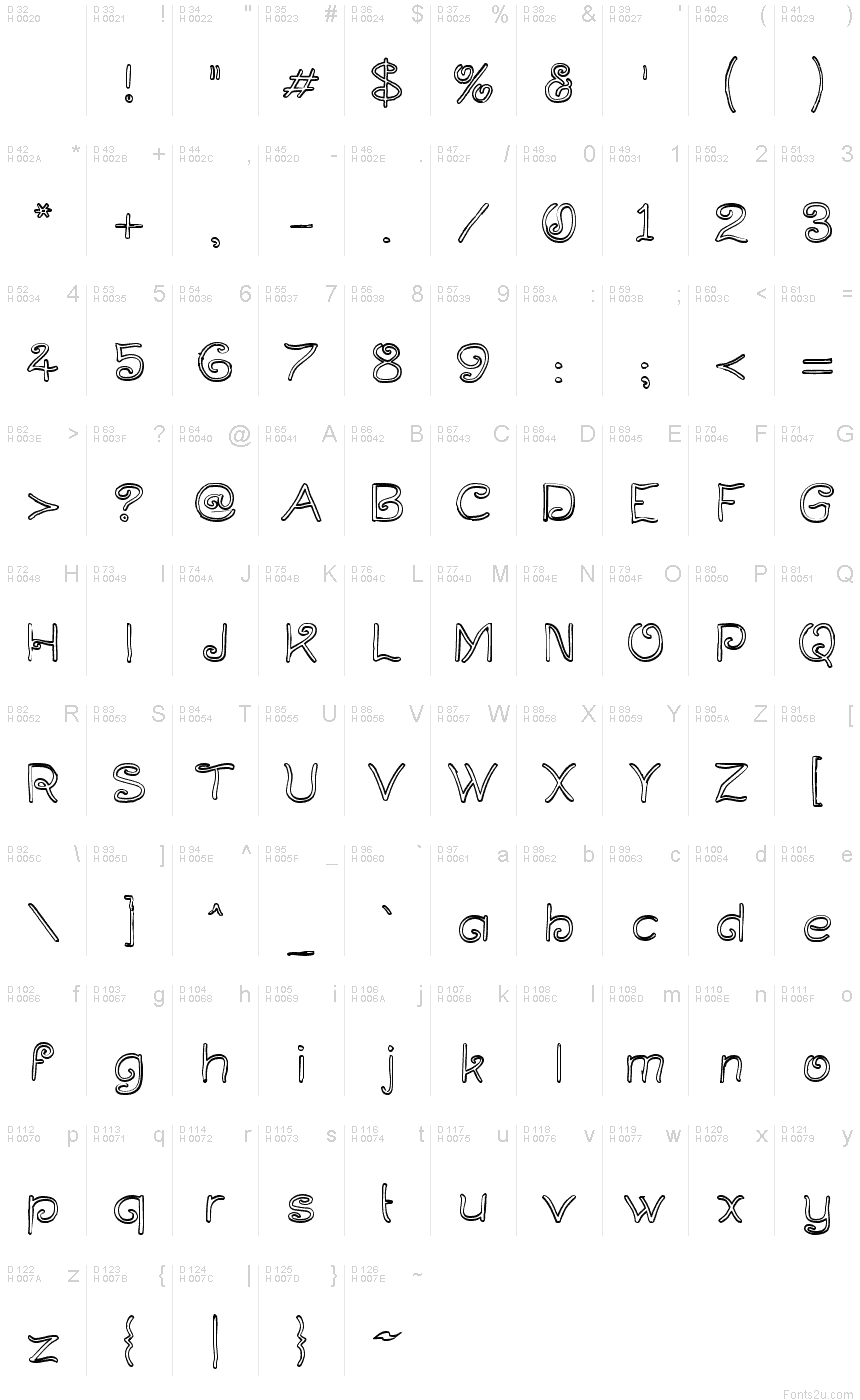
Curlmudgeon Hollow من تصميم GM هو خط مجاني مفرغ (Hollow) بأسلوب الرسم اليدوي ذي الخط المزدوج، مما يضفي لمسة خفيفة ومرحة على الصفحة بدلاً من الثقل. تمنحه الضربات المستديرة والدوامات الصغيرة حيوية مرحة، حتى أن الكلمة القصيرة تبدو نابضة بالحياة، وكأنها رُسمت بجرأة قلم تحديد وابتسامة مشاكسة.
يعمل Curlmudgeon Hollow بشكل رائع في دعوات حفلات الأطفال، ومجموعات الملصقات، وتصميم العلامات التجارية للحلويات، وملصقات الفصول الدراسية، وعناوين سجل القصاصات، وبطاقات المعايدة، والمنشورات الاجتماعية المبهجة. يحب هذا الخط المجاني أن يجد مساحة للتنفس، لذا اجعله أكبر قليلاً وقم بإقرانه بخط sans serif بسيط للنص الأساسي للحفاظ على أناقة ووضوح منحنياته.